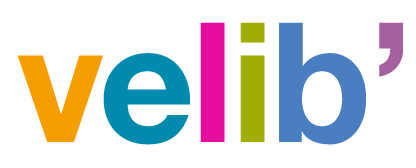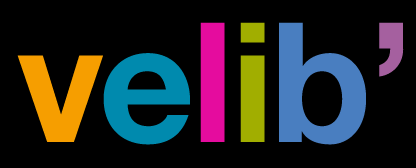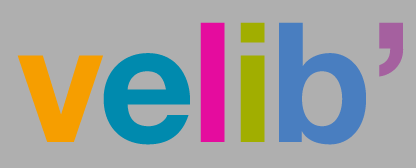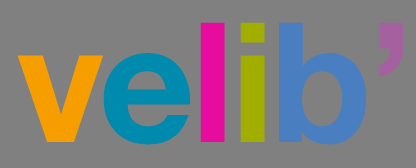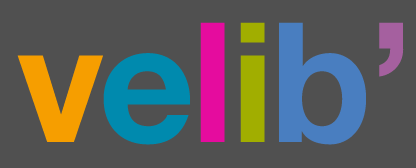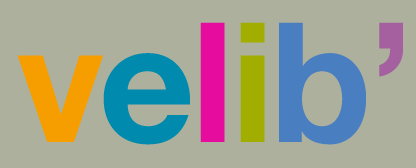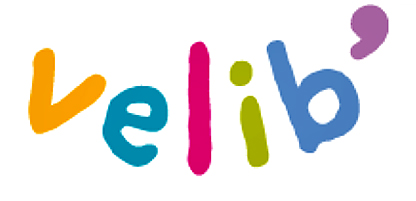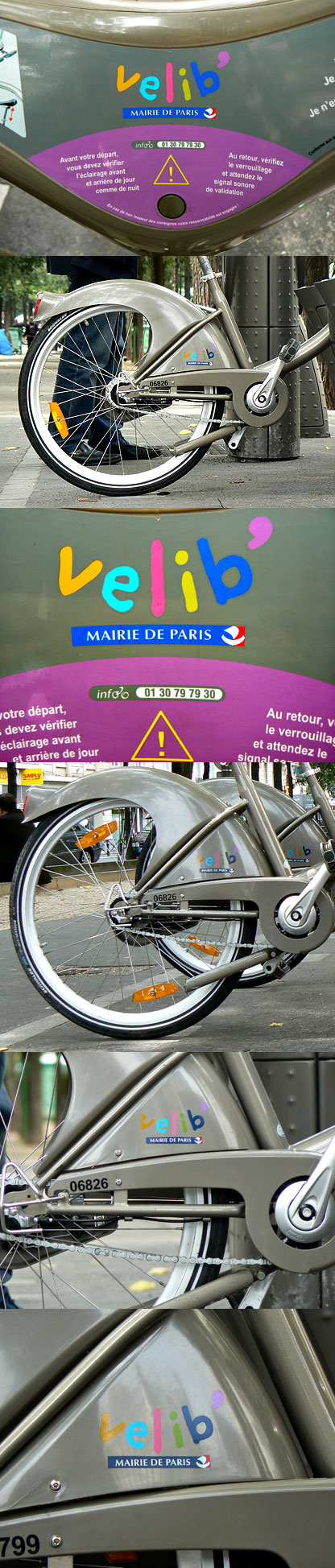
J’aurais pu aussi bien intituler cette chronique, «velib’» des couleurs à la dérive…
Voici sur le site de la Mairie de Paris le logo original dans toute sa splendeur… on sent tout de suite que l’esprit vélo souffle sur les design managers de la Mairie et Decaux Inc. Du moment qu’il s’agit de vélo… point n’est besoin de réfléchir au design stratégie de la marque… et puis de toute façon il n’y a pas de concurrent… enfin pas tout de suite ;-) Le monopole induit l’indolence des responsables qui se croient tout permis du moment qu’ils se considèrent dans l’air du temps, portés par la tendance néo-bio-fin du monde (de l’automobile)… un logo, ça sert à rien… les stations sont là pour faire acte de présence et marquer leur territoire…
Alors je ne vous ennuierai pas avec le choix plus que pénible de la typographie de cette marque… des graphistes fatigués de pédaler avant même d’avoir essayé un branding digne du monde contemporain… Toutefois, si j’avais été à la direction de la comm, voire à la place du Maire, j’aurais confié ce logo à une agence de design Hollandaise plutôt qu’à des Français qui n’ont pas trop la culture du vélo bien encrée…
C’est tout de même curieux que l’on n’ait pas profité de l’occasion alors que l’idée du velib’ est tout de même assez formidable, pour tenter une vraie démarche créative, aussi bien pour le design des vélos (qui ressemblent plus à des chars d’assaut digne de la ligne Maginot qu’à des vélos contemporains et créatifs ) ainsi que pour le design de la marque velib’ qui aurait pu faire l’objet d’une vraie recherche un peu moins amateur que ce manuaire à peine plus élégant qu’un comic sans… terriblement, terrible ;-)
Mais l’objet de ce billet ne concerne pas vraiment la forme mais plutôt le choix de la chromie du logo.
Six signes typographiques, six caractères, apostrophe compris, chacun exprimé dans une couleur différente. Ci-dessous, vous trouverez le logo qui figure sur le site de velib’. Sur fond blanc. Puis juste en-dessous vous trouvez six photographies de détail sur les vélos où l’on s’aperçoit que les couleurs employées n’ont plus grand chose à voir avec l’original. Si l’orange du <v> est à peu près respecté, le <e> est totalement trahi pour un cyan <descendu> à 30-40%, de même que le <l> pour un magenta plus flashy, un <i> qui hésite entre un jaune et un vert plus foncé que l’original, quant au <b> il est franchement différent, tantôt proche d’un blue reflex, tantôt d’un Pantone 314C. Qu’est ce qui ne fonctionne pas dans tout cela…? La réponse est simple et s’impose au premier regard…
L’utilisation de six couleurs vives, primaires ou complémentaires, fonctionne bien sur fond blanc et sur fond noir — Cf les essais que j’ai réalisé ci-dessous en Helvetica Neue Bold (afin de m’extraire des contingences typographiques en prenant un caractère assez neutre (d’après Wim Crouwel)).
Mais dès lors que vous plaquez ces couleurs sur un fond gris, les teintes viennent à lutter avec les equidensités similaires… Pourquoi ce phénomène… Je ne vous apprendrai pas qu’une couleur est constituée de deux paramètres, sa teinte et sa tonalité…
La première concerne la pigmentation ou longueur d’onde sur le spectre lumineux. La deuxième, le ton concerne sa densité ou sa valeur exprimée sur une échelle de gris. Pour vous rendre compte du phénomène, il suffit de regarder le logo original en clignant les yeux jsuqu’à voir disparaître la vivacité des couleurs et ne plus voir que des valeurs de gris… En l’occurence c’est assez difficile, du fait de la vivacité des couleurs… mais vous pouvez tout de même essayer… Ce n’est pas probant?
Alors je vais maintenant vous inviter à en faire de même avec mes essais du logo sur les fonds gris ci-dessous… Où l’on aperçoit que, sur les figures {3} {4} et {6}, la tonalité du fond vient systématiquement en équidensité avec l’une ou l’autre des lettres colorées du logo. Ce qui en rend la lecture parfaitement illisible. La figure {6} reprend d’ailleurs approximativement la couleur de fond d’origine de la peinture des velib’s.
Ce qui fait que l’on peut maintenant deviner sans trop de difficulté que la création d’origine n’avait sans doute pas prévu la déclinaison du logo sur autre chose que fond blanc ou noir. Les tests n’ont assurément pas du être fait, sinon même un enfant de quatre ans vous aurait dit que cela ne fonctionnait pas. Il suffit de regarder les photos, les logos sont illisibles sur les cadres.
Bon j’arrête là mes critiques pour ce jour, et ne croyez surtout pas que je n’aime pas le concept de ces vélos… une véritable révolution urbaine, qui connaîtra j’en suis sûr un succès grandissant. Mon regret au fond est simplement de voir qu’une fois de plus les pouvoirs publics ont raté l’occasion de marquer l’évènement par une vraie création graphique digne de ce nom.
Expérience… clignez des yeux en examinant chacun de ces logos sur un fond différent, et vous verrez les seuils d’illisibilité apparaître dès lors que la densité du fond se rapproche de la tonalité de l’une ou l’autre des lettres.
Les photographies sont d’Elisabeth Gabor
pour ceux qui se demandent d’où provient la création de ce logo. C’était le sujet du CAPLP (concours de l’éducation national d’acces à la fonction d’enseignant) de 2007, que j’ai moi même passé. Il ne nous a jamais été dit que le meilleur résultat serait exploité par la suite ! je ne sais pas si celui qui a créé ce logo a même été rémunéré ?? Mais je n’ai fait le constat de cette “réussite” qu’en relisant le rapport de jurys de concours 2007, édité par le sceren, dernierement. A lire page 25 de ce rapport : le jury à apprécié …des propositions d’accroche, par exemple : ….”velib” (en réponse au dispositif lyonnais ‘velov’ )